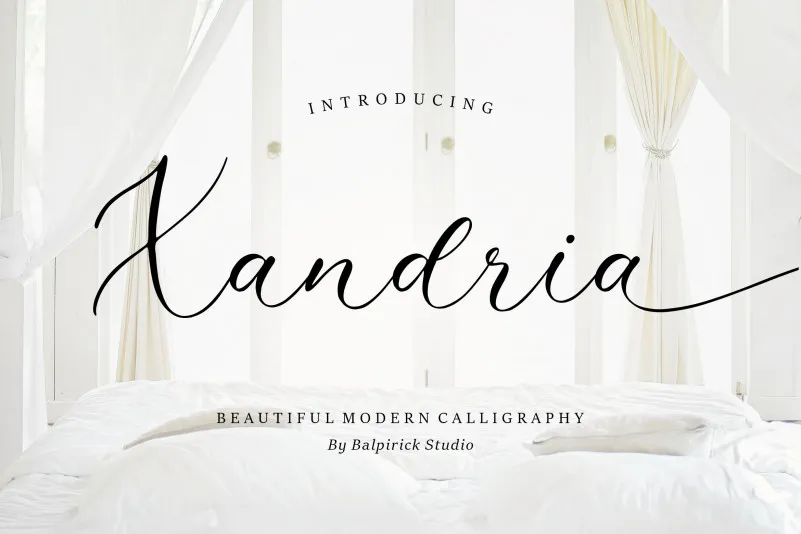
Xandria Font – Download Grátis
A Xandria é uma fonte de escrita chinesa perfeita para vários usos visuais em design gráfico. Seja você criando embalagens de produto ou projetando marcas, a Xandria tem sua versão suave e elegante que se adequará à sua necessidade. Além disso, ela é excelente quando utilizada em publicações de revistas, redes sociais, para expressar mensagens importantes nas camadas de design das casamentos, ou simplesmente como um recurso aprimorado para qualquer projeto visual. Com o designer balpirick, você encontrará uma fonte que se adapta aos mais variados estilos e necessidades do seu trabalho.